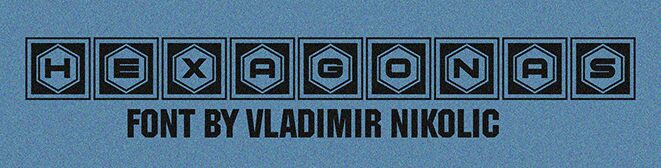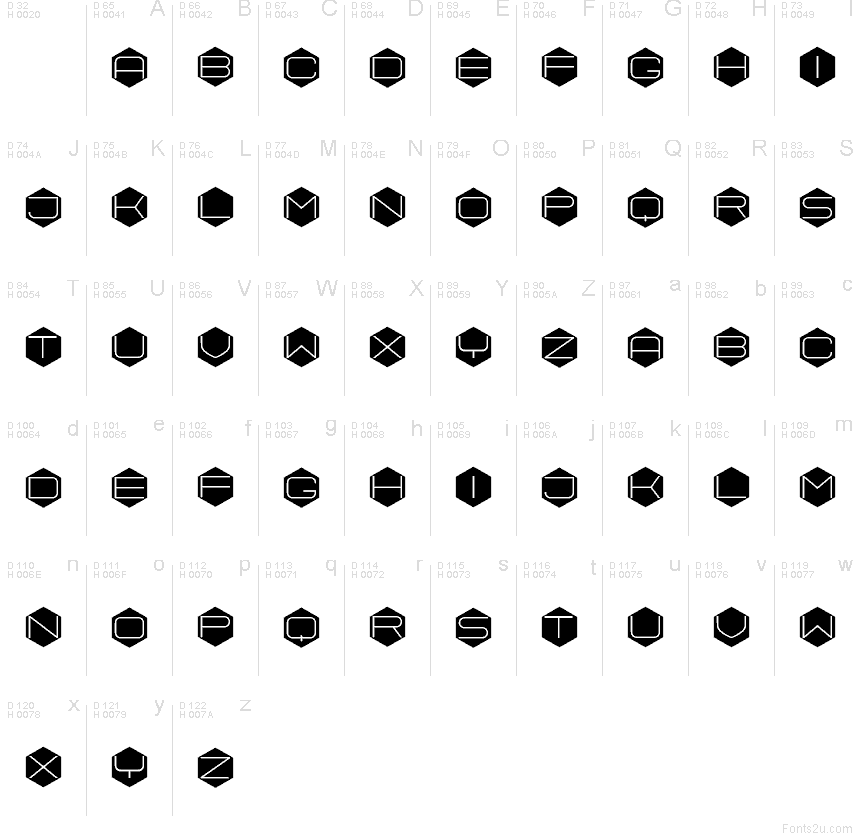
Hexagonas Condensed Regular
Hexagonas Condensed de Vladimir Nikolic es una tipografía decorativa display gratuita con un estilo geométrico basado en el hexágono. Cada carácter está enmarcado por un contorno afilado de seis lados, con cortes interiores rectos y esquinas cuadradas que dotan a toda la familia de un ritmo facetado y constructivista.
Hexagonas Condensed funciona muy bien en títulos de pósteres, branding tecnológico, portadas de álbumes, logotipos y señalética decorativa donde un patrón geométrico rígido sea parte esencial del diseño. Sus formas compactas y su marco hexagonal repetitivo la hacen ideal para palabras cortas, insignias, arte de portada y titulares que requieran una estructura robusta y con patrón, sin ornamentos adicionales.